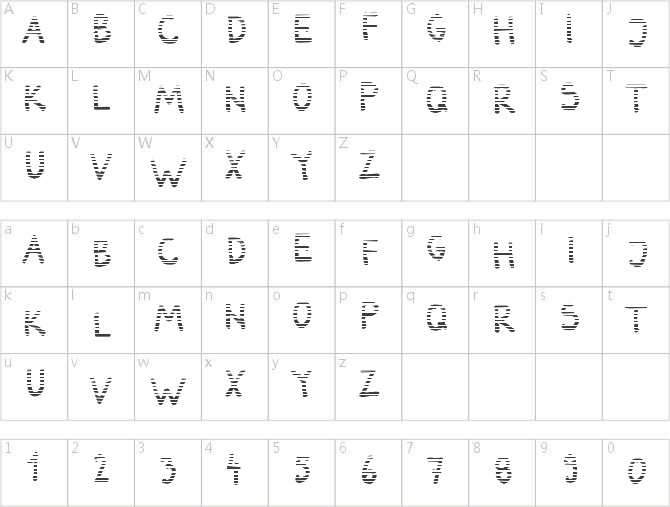
字体名称: Darbog
Darbog gradient bold
Darbog gradient bold介绍
Darbog gradient bold字体字库是一款让人赏心悦目、百看不厌的英文字体,适合各类广告和产品包装设计应用,字体大小0.21MB,格式为ttf字体,上传用户是Elieen,作者/版权方为未知